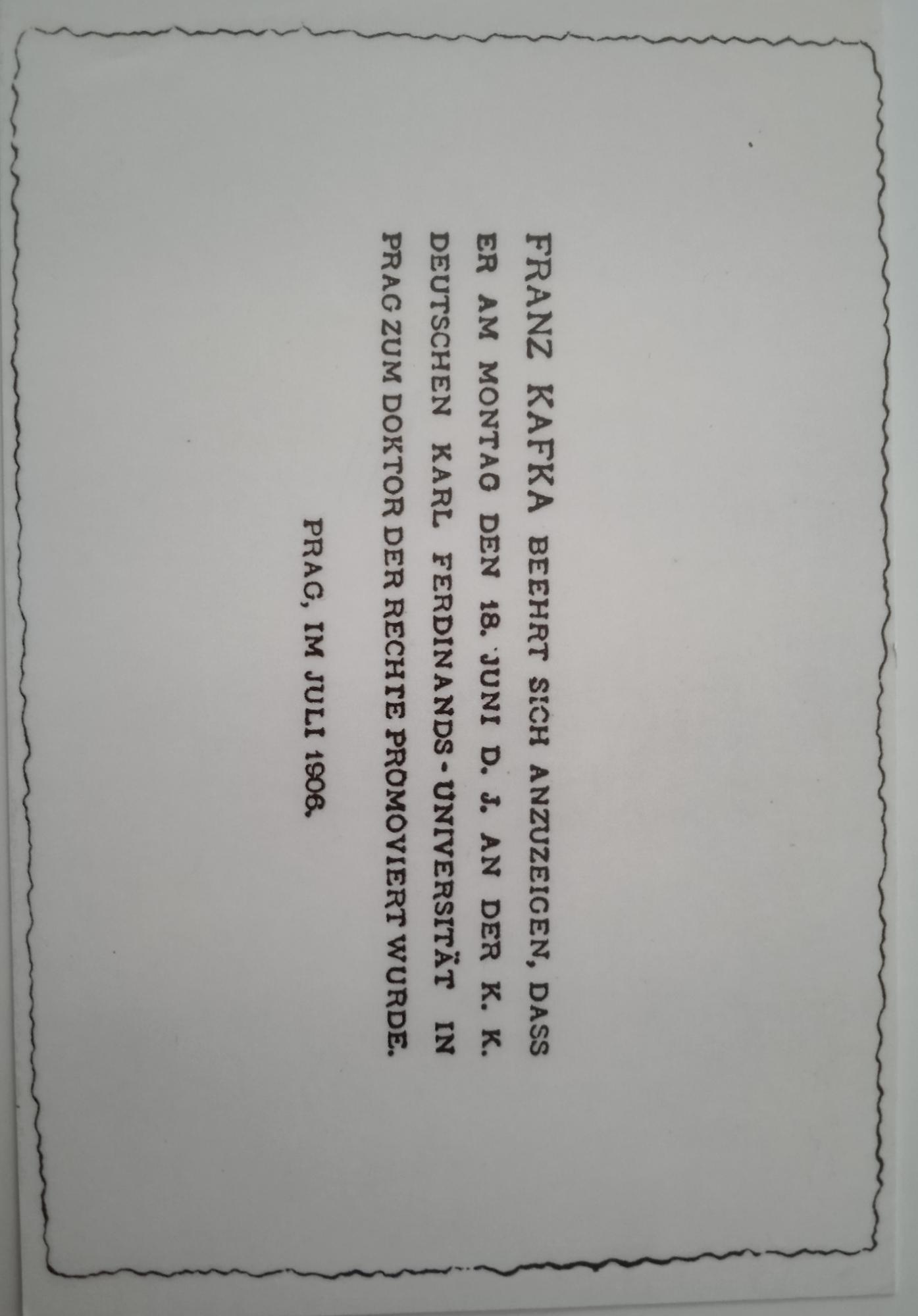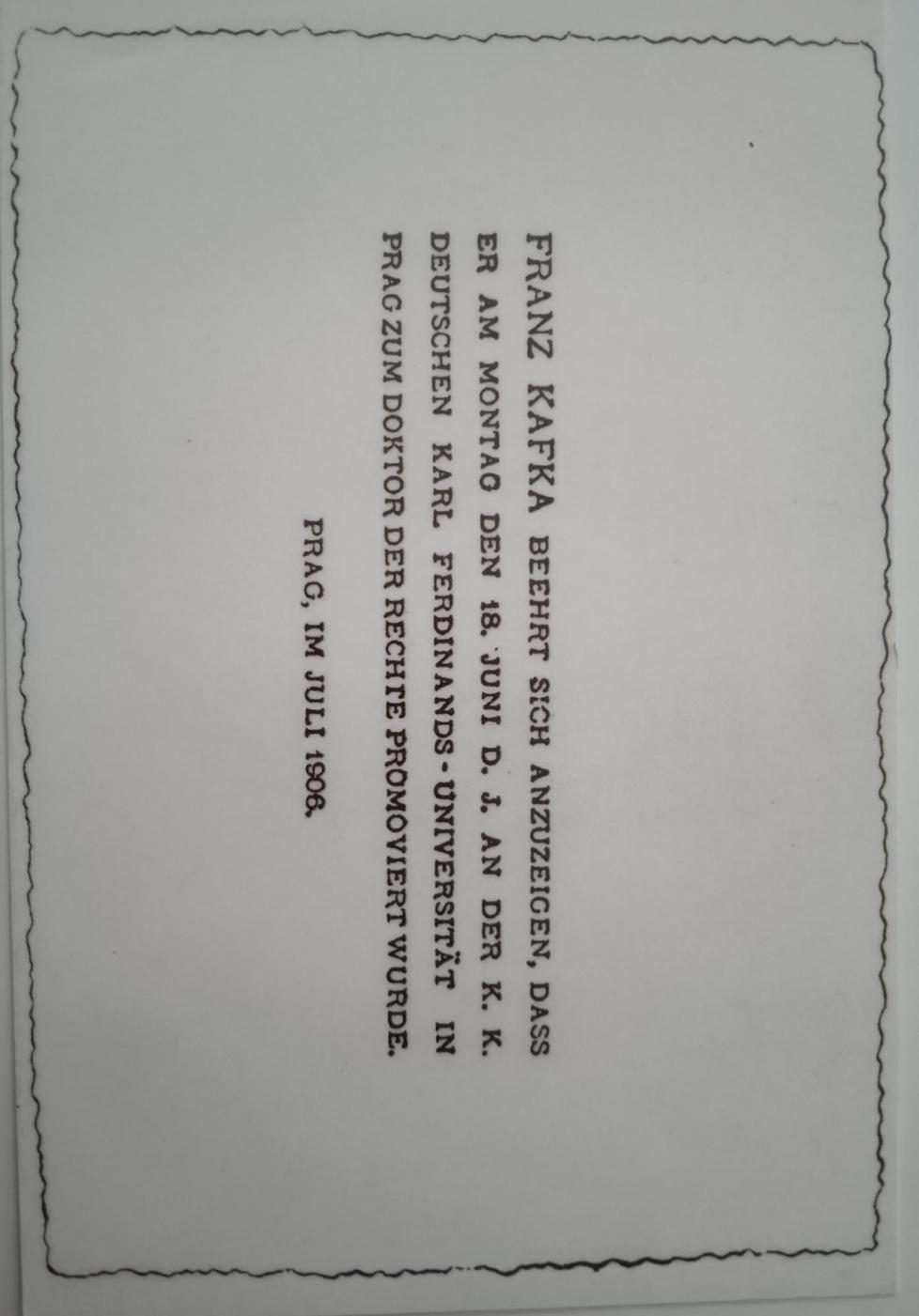
Kafkas Promotionsanzeige
Für Profis sicherlich kein Problem... Was für ein Schrifttyp ist das hier?
Hallo Nils, willkommen im Forum. So einfach wird das wohl nicht werden, zumal die Qualität des Fotos zu wünschen übrig lässt. Auffällig an der Schrift ist das R mit seinem tiefreichenden Fuß, das K und das F mit dem seinem weiten Arm. Eine digitalisierte Schrift kann ich nicht nennen, und um herauszubekommen, welche Bleisatzschrift das ist, müsste man Schriftmusterbücher wälzen. Vielleicht weiß eine der Forenkolleginnen oder einer der Forenkollegen mehr.